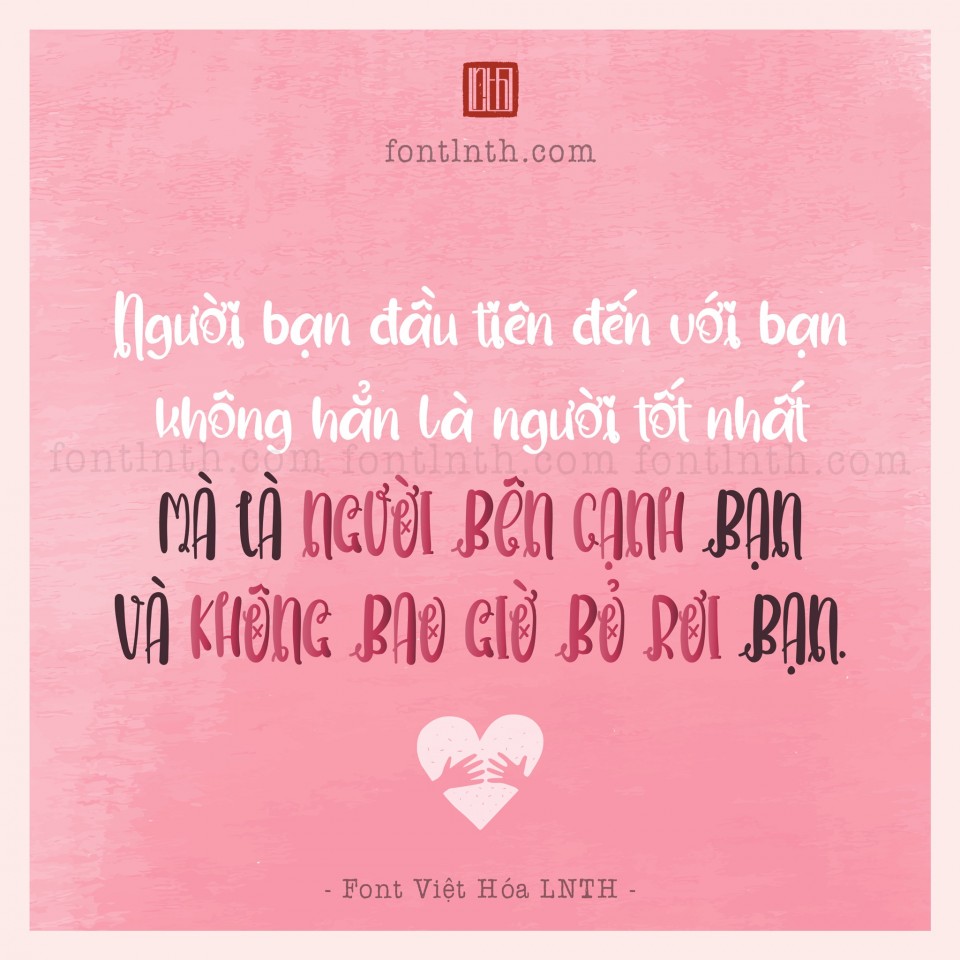
Giới thiệu về Font việt hóa LNTH Excites Squirrell
Trong thế giới thiết kế đồ họa dành cho học đường, việc lựa chọn một bộ Font Chữ phù hợp đóng vai trò cực kỳ quan trọng. Font việt hóa LNTH Excites Squirrell là một cái tên nổi bật, mang đến làn gió mới đầy sự vui tươi và sáng tạo. Đây là bộ font được lấy cảm hứng từ những nét vẽ tay tinh nghịch, rất thích hợp cho các dự án liên quan đến trẻ em và giáo dục tiểu học. Với các đường nét bo tròn và cấu trúc chữ cân đối, bộ font này không chỉ tạo cảm giác thân thiện mà còn đảm bảo tính dễ đọc tối đa trên nhiều chất liệu khác nhau.
Tại sao nên chọn Font việt hóa LNTH Excites Squirrell?
Đặc điểm lớn nhất của Font việt hóa LNTH Excites Squirrell chính là sự linh hoạt. Bộ font đã được tối ưu hóa tiếng Việt hoàn chỉnh, giúp các thầy cô giáo và học sinh dễ dàng soạn thảo văn bản mà không lo lỗi font hay thiếu dấu. Sự kết hợp giữa phong cách hiện đại và nét vẽ hồn nhiên giúp bộ chữ này trở thành lựa chọn hàng đầu cho các bài giảng trình chiếu Powerpoint, áp phích sự kiện trường học hoặc trang trí báo tường. Ngoài ra, tính thẩm mỹ cao của nó còn giúp kích thích sự chú ý của học sinh trong quá trình tiếp thu kiến thức.
Cách ứng dụng Font việt hóa LNTH Excites Squirrell hiệu quả
Để tận dụng tối đa vẻ đẹp của font chữ này, người dùng nên kết hợp với những tông màu sáng như vàng, xanh lá hoặc cam. Trong các bìa sách bài tập hay thiệp chúc mừng, bạn có thể sử dụng kích thước chữ lớn để làm nổi bật tiêu đề chính. Font việt hóa LNTH Excites Squirrell cũng hoạt động tốt khi phối cùng các phông chữ không chân (sans-serif) đơn giản để tạo nên sự cân bằng cho tổng thể bố cục thiết kế. Hy vọng bộ Font Miễn Phí, Font Việt Hóa, Font việt hóa LNTH Excites Squirrell này sẽ giúp bạn có những tác phẩm sáng tạo và chuyên nghiệp hơn.